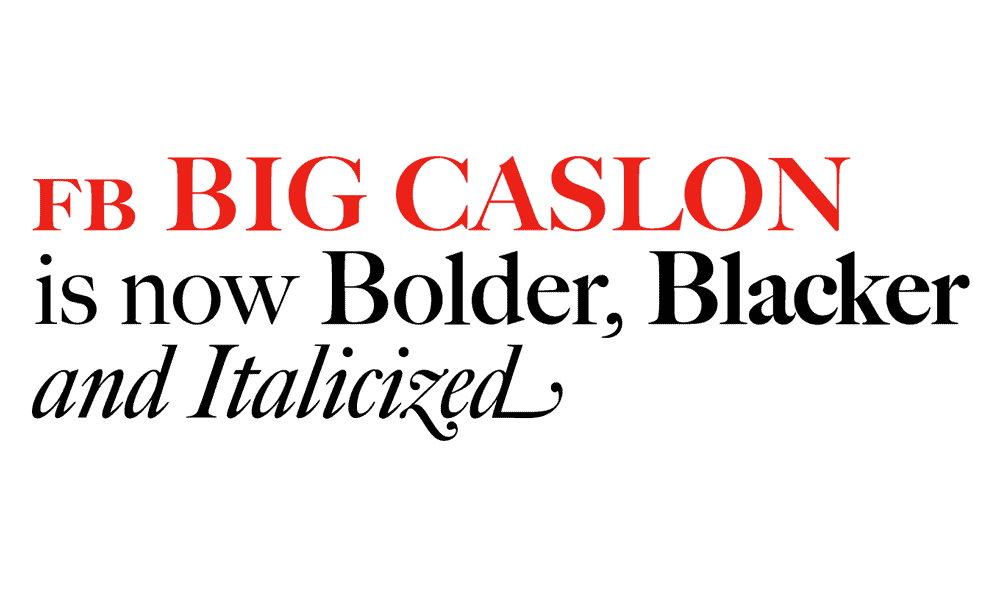
Caslon является шрифт с засечками, созданный Уильямом Caslon в XVIII — го века.
Характеристики
Caslon включает вариации регулярности, типичные для голландских шрифтов переходного периода в стиле барокко. Для него характерны довольно короткие косяки, крутые засечки, относительно умеренный контраст, прочная текстура и дискретная модуляция линий. Апекс концов А в вогнутом расширении, G не имеет шпор . Курсив имеет каллиграфический ритм, буквы A, V и W имеют слегка натянутый наклон. Строчные курсивы p, q, v, w и z имеют окончания каллиграфического типа.
История
Самые ранние размеры Caslon относятся к 1722 году. Caslon известен как самый первый оригинальный шрифт в английском стиле, хотя некоторые историки типографии, такие как Стэнли Морисон или Альфред Ф.
Джонсон, ученый, учившийся в Британском музее, настаивают на очень близком сходстве модели Каслона с современными шрифтами, использованными Oxford University Press и гравированными Дирком Воскенсом, а также с другими голландскими шрифтами Кристоффелем ван Дейком .
Голландские гарнитуры использовались тогда подавляющим большинством типографий в Англии : Oxford University Press использовала гарнитуры, выгравированные голландским основателем Воскенсом. Cambridge University Press только что получил от Нидерландов воколо 52 серий алфавитов, произведенных Ван Дейком. Годом ранее, в 1697 году, она использовала «Римлянам и курсивом» Ван Дейка для издания Gratulatio Cantabrigiences . Персонажи Ван Дейка и Воскенса также используются для Уильяма Харисона, Вудсток Парк, Тонсон, 1706 год.
Карьера Уильяма Кэслона задокументирована позже (Роу Мор около 1778 года, Джон Николс в 1782 году, затем в 1815 году), существует относительная неопределенность относительно точного происхождения Каслона.
По словам Николса, покрой первых шрифтами Уильяма Caslon был араб, для Псалтири (Псалтырь) в 1725 году, на иврит работ Джона Селдена в 1726 году, Коптский для Пятикнижия двуязычного D г Дэвида Уилкинс на латинском и древнееврейском 1731, и это не дает никаких указаний относительно первых размеров Caslon римским шрифтом и курсивом.
По словам Николса, «[Каслон] вырезал эти прекрасные английские шрифты, которые использовались для печати работ Селдена в 1726 году» . Николс считает, что эти символы намного превосходят современные голландские шрифты, которые использовались в английских произведениях того времени. Именно эта атрибуция ставится под сомнение исследователями, потому что римлянин, который используется в этой работе, Гарамонд, использованный в первом томе и частично во втором, будет идентичен тесту, хранящемуся в Британском музее под названием Groote Mediaan Romyn, априори датированный 1715 годом.
Этот шрифт, который также занесен в наследие вдовы Воскенса, впервые использовался в Амстердаме в 1684 году.
Из его ассоциации с Уильямом Бойером можно определить самые старые размеры Caslon римским шрифтом и курсивом:
- 1725: Римский и курсив, pica body (эквивалент 12 body), в примечаниях Анакреона на греческом и латинском языках.
- 1726: Римский и курсив, body pica, в Reliqu Baxterianæ .
- 1730: Римский шрифт и курсив, английский кегль (эквивалент 14 кегля), в предисловии к « Хроникам королей Англии» Ричарда Бейкера. Текст работы находится в Caslon Pica.
Шрифты, вырезанные сначала Уильямом Кэслоном, а затем его сыном, являются производными, очень близкими к шрифтам Ван Дейка, тонко измененными характеристиками и перебалансированными, чтобы соответствовать ожиданиям своих клиентов.
Ограбления Caslon были широко распространены по всей Британской империи, включая Северную Америку . По этому поводу, например, окисление, которое могло быть вызвано опасными условиями во время трансатлантического плавания, было признано ответственным за частое низкое качество североамериканских гравюр этого периода: на самом деле было бы необходимо также принять во внимание условия хранение и транспортировка на месте.
Тем не менее, шрифты Caslon были сразу же оценены, и они являются шрифтами многих исторических документов, включая официальное распространение Декларации независимости Соединенных Штатов . После смерти Уильяма Кэслона использование его шрифтов сократилось, но они пережили возрождение в контексте движения искусств и ремесел в Великобритании .
Каслоны широко используются и сегодня.
В конце 19 века в технологии набора текста произошли три основных изменения, затронувшие шрифт Caslon. Начиная с введения горячего шрифта, а затем развития фотонабора в 60-х и 70-х годах, мы увидели недавнее изменение цифровых шрифтов, которое началось в середине 1980-х годов. Все эти технологические изменения привели к изменению дизайна шрифта Caslon, некоторые из которых очень мало похожи на исходный шрифт, за исключением засечек и названия.